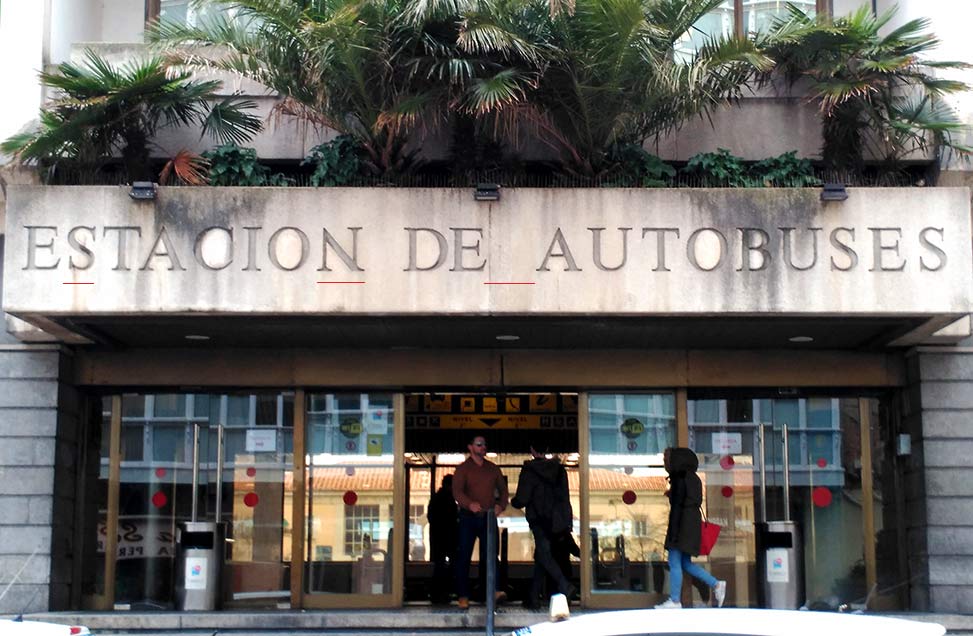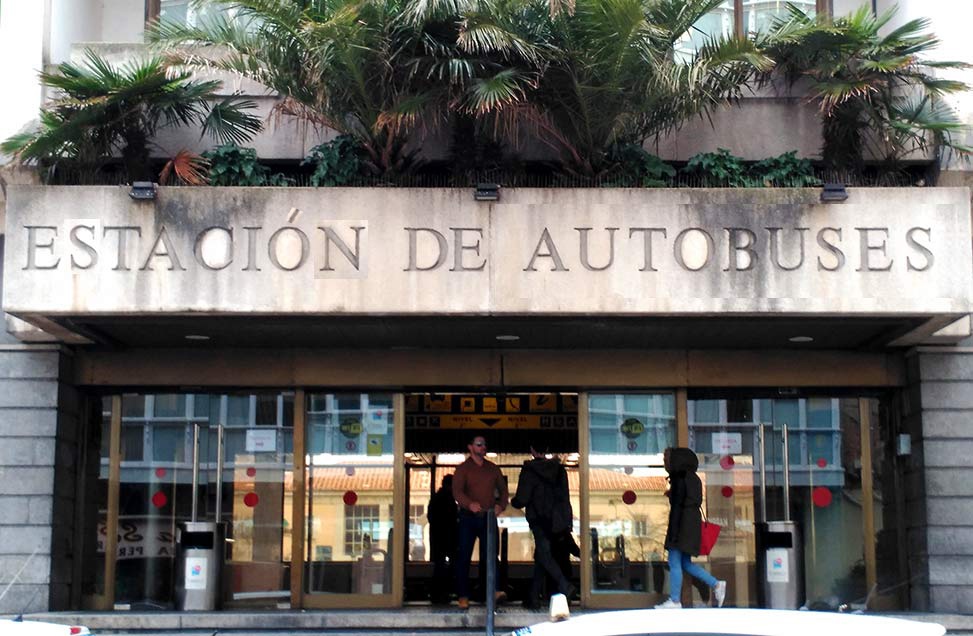
Errores en la inscripción de la Estación de Autobuses
Por la Estación de Autobuses de Santander cada día pasan cientos de personas. En el dintel de la entrada principal, una gran inscripción grabada en la piedra nos da la bienvenida, con una tipografía clásica posiblemente una Times. Pero, ¿os habéis percatado de que hay dos errores en una misma palabra, incluso podríamos hablar de un posible tercer error en la inscripción y otro error gramatical?
A continuación señalamos los errores:
• 1) la primera «S» de estación está invertida, su forma choca con el resto de eses que hay.
• 2) la «N» de estación está invertida, ya que se apoya en la serifa.
• 3) el tercer error le podríamos considerar en el espacio que hay entre «de» y «autobuses», si lo comparamos con el primer espacio entre «estación» y «de»
• y este puede ser de bonus. Gramaticalmente la acentuación de «Estación».
De momento mientras no cambie, siempre podréis pasar y verlo, y enseñárselo a la gente. Es curioso como nuestro cerebro a veces nos la juega y nos hace ver que todo está correcto y que obviamente leemos por encima y construimos las palabras. Aquí tenéis como sería en realidad, corrigiendo esos fallos.